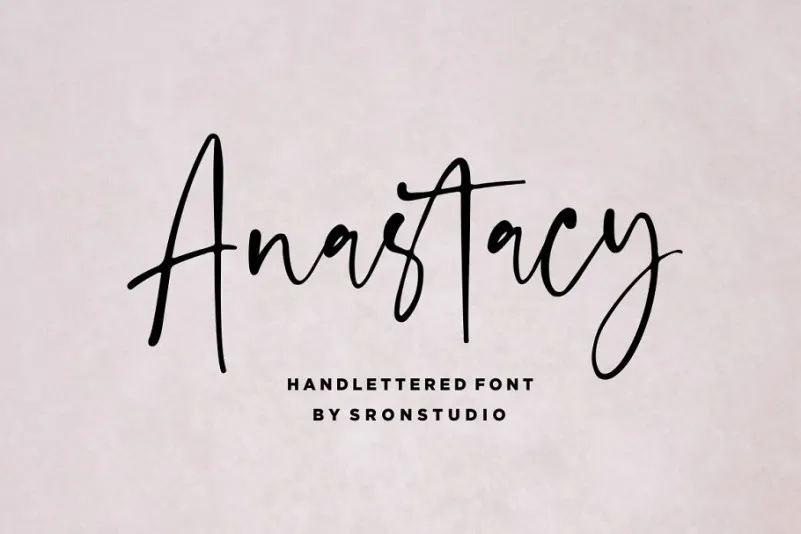
Anastacy Handlettered Font – Download Grátis
Esse é Anastacy Handlettered Font, uma elegante fonte script feita para designers apaixonados por design artesanal. Introduzida no mercado como uma opção única para quem busca um toque natural na ilustração de texto, esta fonte traz a essência da escrita à mão em cada letra, perfeita para projetos variados. Anastacy é ideal para criações que exigem tanto sofisticação quanto charme, especialmente para aplicativos como logotipos, convites, embalagens, produtos e até mesmo para publicações nas redes sociais. Esta fonte também inclui alternativas contextualizadas, símbolos multilíngues, números e pontuação, garantindo um amplo leque de opções para seus projetos de design. Se você está procurando por uma fonte que combine elegância artesanal com a necessidade de versatilidade, Anastacy Handlettered Font é definitivamente o tipo de recurso que precisa no seu arsenal de ferramentas gráficas.